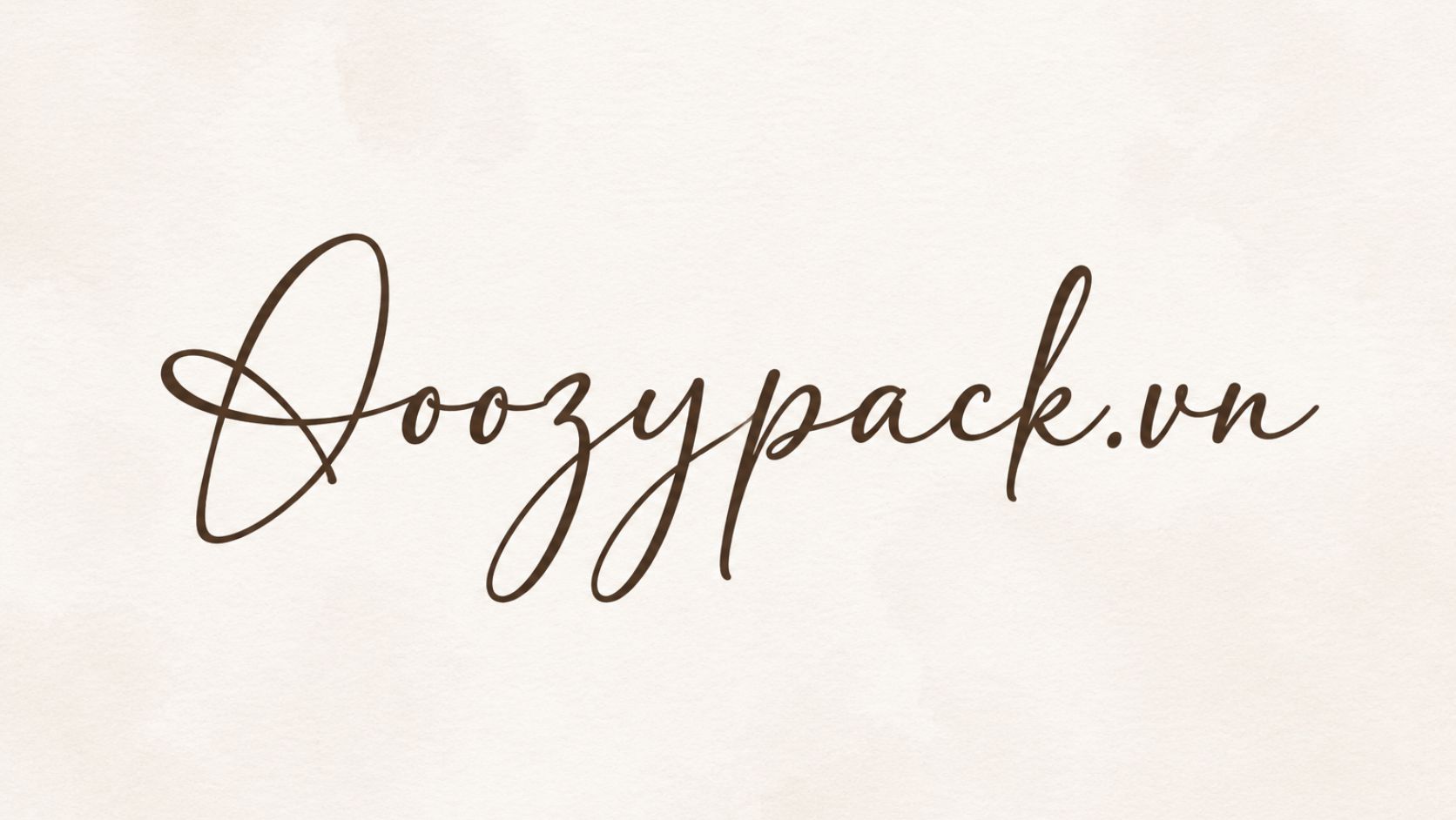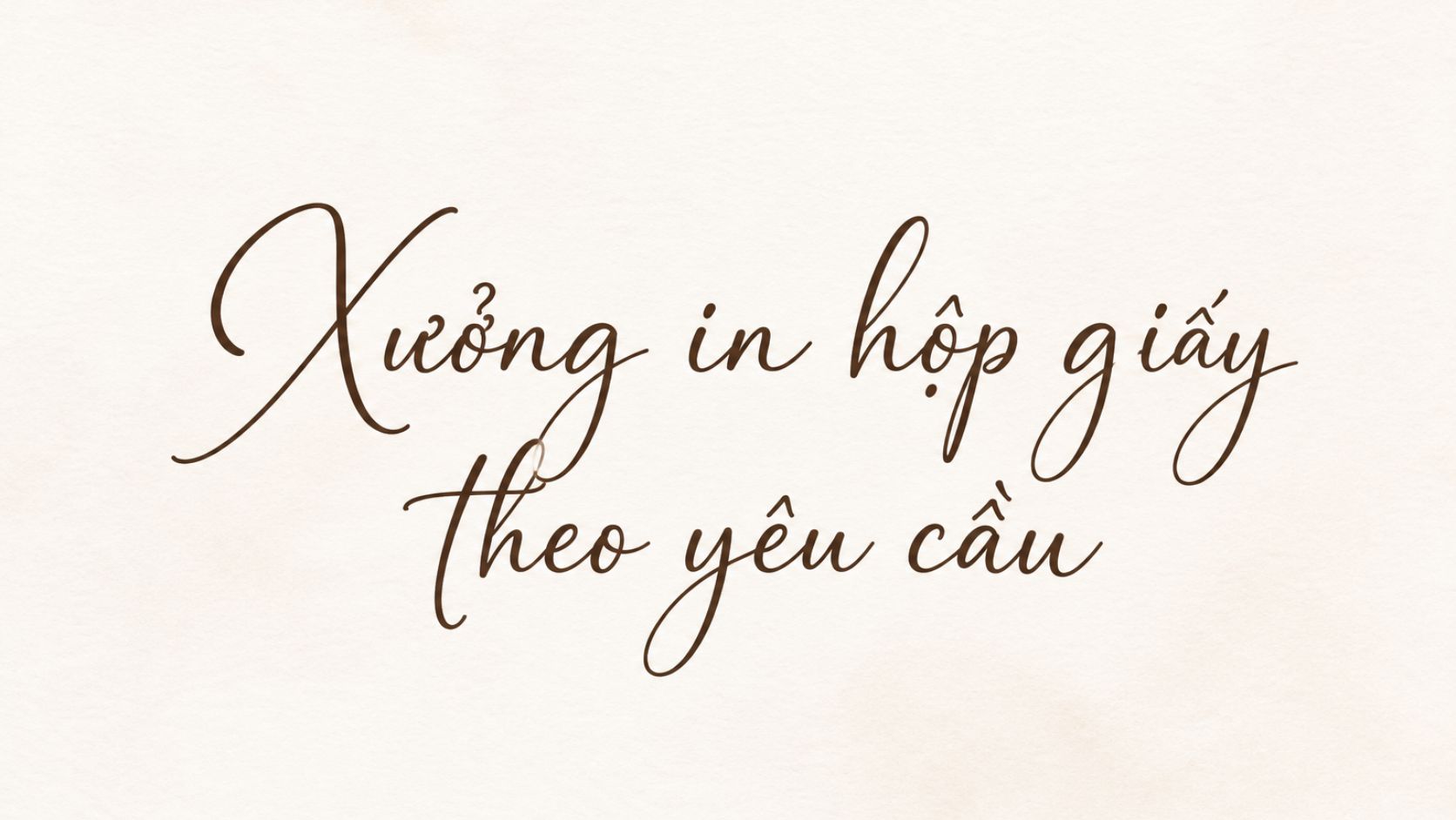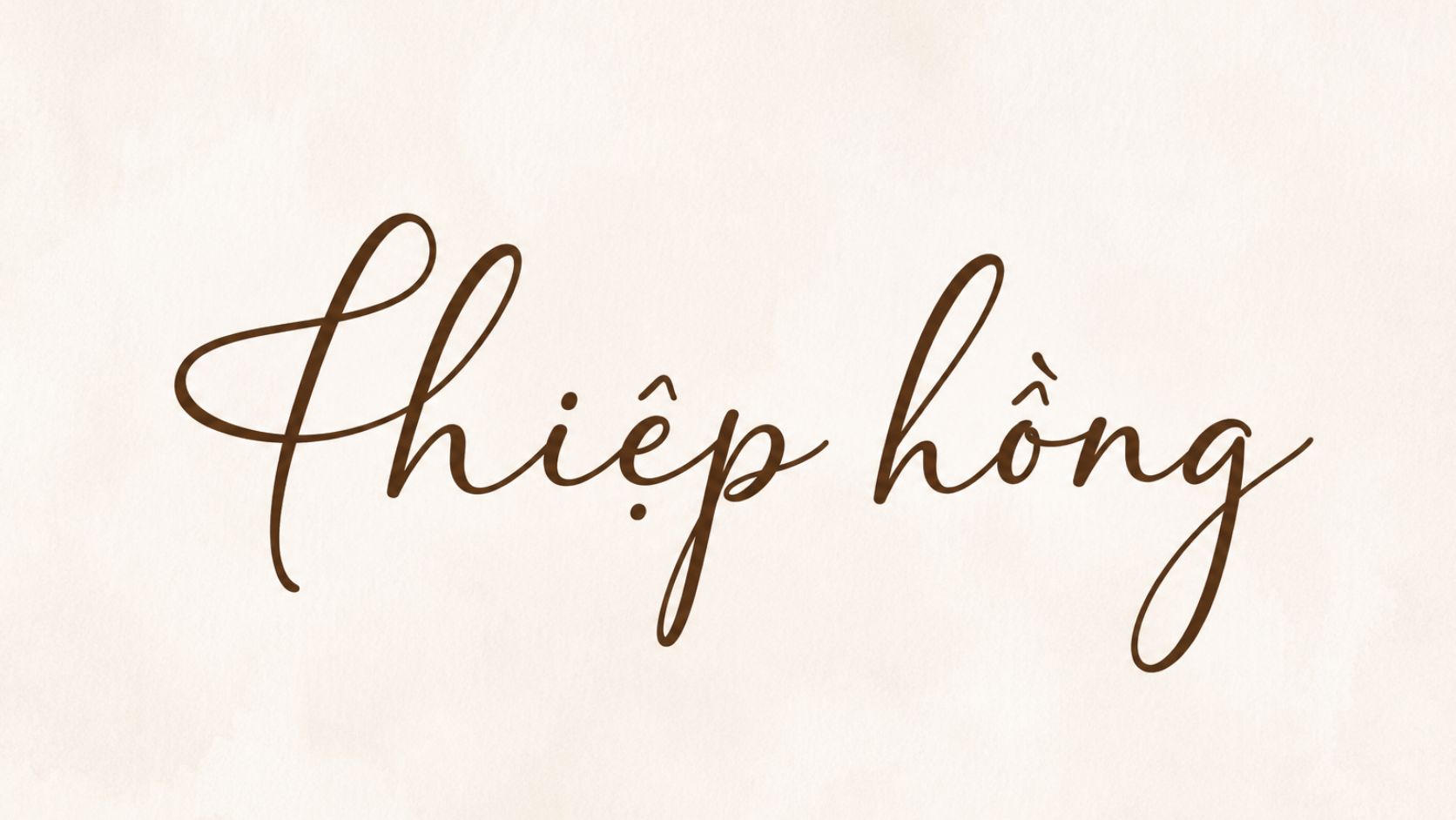
Adelia font Việt hóa là bộ font script hiện đại với những đường nét viết tay mềm mại, phóng khoáng, mang lại cảm giác vui tươi và đầy sức sống cho các thiết kế nghệ thuật. Đây là lựa chọn hàng đầu của các designer khi thực hiện dự án về bao bì mỹ phẩm, thiệp mời, hoặc logo thương hiệu cần sự nữ tính và tinh tế. Doozypack.vn chia sẻ bộ file tải Adelia font Việt hóa chuẩn, hỗ trợ đầy đủ các ký tự tiếng Việt giúp bạn sáng tạo không giới hạn mà không lo lỗi dấu.
02 Đặc điểm nổi bật của bộ font Adelia Việt hóa
Adelia không chỉ là một phông chữ script thông thường mà còn chứa đựng sự kết hợp khéo léo giữa phong cách Brush và Calligraphy hiện đại. Việc hiểu rõ các đặc điểm của font sẽ giúp bạn ứng dụng hiệu quả hơn trong thiết kế bao bì và ấn phẩm truyền thông.
Phong cách thiết kế Brush Script phóng khoáng
Adelia gây ấn tượng nhờ sự tương phản giữa những nét đưa bút dày và mỏng đan xen một cách tự nhiên. Cấu trúc chữ có độ nghiêng vừa phải, tạo cảm giác như được viết bằng cọ mực thật, giúp các bản thiết kế trở nên gần gũi và có hồn hơn. Font chữ này cực kỳ phù hợp cho những thương hiệu hướng đến sự trẻ trung, thân thiện và mang tính cá nhân hóa cao.
Bộ ký tự mở rộng (Glyphs) đa dạng
Một trong những điểm khiến các designer tìm kiếm bản download font Việt hóa Adelia chính là hệ thống Glyphs phong phú. Font cung cấp nhiều ký tự thay thế (alternates) và các nét uốn lượn (swashes) ở đầu và cuối chữ cái. Điều này cho phép bạn tùy biến các từ ngữ trở thành một tác phẩm typography độc đáo, đặc biệt hữu ích khi thiết kế logo hoặc tiêu đề bao bì sản phẩm quà tặng.
04 Ứng dụng font Adelia trong thiết kế bao bì và in ấn
- Tem nhãn sản phẩm: Adelia mang lại vẻ đẹp thanh lịch cho các dòng sản phẩm handmade, serum, hoặc kem dưỡng da thiên nhiên.
- Hộp giấy quà tặng: Khi kết hợp Adelia (làm điểm nhấn chính) với một font chữ không chân (Sans-serif) đơn giản cho phần nội dung phụ, vỏ hộp sẽ đạt được sự cân bằng và sang trọng.
- Túi giấy thời trang: Tên thương hiệu in bằng font Adelia trên nền túi giấy Ivory cán mờ tạo cảm giác cao cấp và thời thượng.
- Thiệp và bao lì xì: Các nét chữ bay bổng của Adelia rất phù hợp cho các dịp lễ Tết, Trung thu hoặc thiệp cảm ơn đính kèm trong hộp sản phẩm.
03 Lưu ý kỹ thuật khi sử dụng font Adelia để in ấn thực tế
- Tránh nét quá mảnh khi ép kim: Font Adelia có một số nét vuốt cực mảnh. Nếu bạn có ý định ép kim (hot stamping) lên giấy có gân sâu, những nét này có thể bị đứt đoạn hoặc không bám kim. Hãy kiểm tra độ dày nét chữ trước khi xuất file.
- Kiểm tra khoảng cách chữ (Kerning): Do đặc thù là font viết tay, các chữ cái cần có sự liên kết mượt mà. Bạn nên điều chỉnh thủ công khoảng cách giữa các cặp chữ cái đặc biệt để đảm bảo tính thẩm mỹ cao nhất.